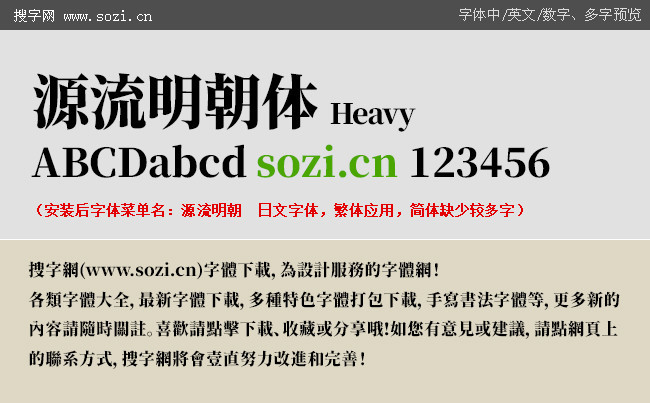
源流明朝Heavy
搜字网给大家提供一款源流明朝Heavy中文字体下载,源流明朝体源自思源宋体,风格较原字体改变较大,尤其是勾的笔画更加具有线条感,使字型看起来更有力道。汉字宽度稍微压缩,显得比原始的思源宋体要稍微瘦长。并且在横笔的起笔与竖笔的起笔、收笔,全都加上粗细变化,仿佛重现铅字的压印感,文字较有文学感、人文气息。适用于大标题、包装设计、海报设计等应用。